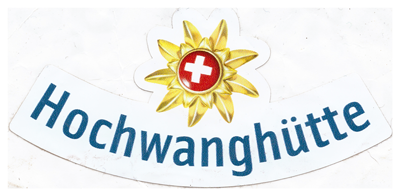
Grüße aus der Schweiz. Welche Typo mit leichten "Elefantenfüßen" kann das sein?
Aus dem Ski-Urlaub bringe ich diesen Aufkleber und einen kleinen Freundschaft-Auftrag mit. Doch auch beim durchblättern im fontExplorer von fast 4k Schriften bin ich nicht fümdig geworden. Habe ich eine Sehschwäche? Bislang wurde mir nichts dergleichen diagnostiziert.
Die Elefantenfüße kommen von der Verzerrung. Das ist kein Rundsatz, sondern wurde wohl im Illustrator o.ä. verkrümmt.
In heutigen Zeiten mit mehreren hunderttausend Schriften auf dem Markt, würde ich Dir von so einer Herangehensweise auch abraten. ;-) Lieber in diese Trickkiste greifen oder den Urheber ermitteln und fragen. :-)
Obwohl mir die Schrift sehr bekannt vorkommt, komme ich aber auch nicht drauf und konnte bisher auch im Netz nichts Identisches finden.
Ein ähnliches Formenprinzip findest Du unter anderem bei der FF Fago, FS Truman, Camingo Dos, Allumi, FF Utility, Klavika, Riga oder Yalta Sans – falls Dir das auch schon hilft (nicht vom komplexen g abschrecken lassen, das gibt es spätesten in der Pro-Version bei vielen auch in der einfachen Form).
nicht ganz genau die Schrift aber ziemlich ähnlich ist, ITC Quay Sans. Schau selbst auf identifyfont.com.